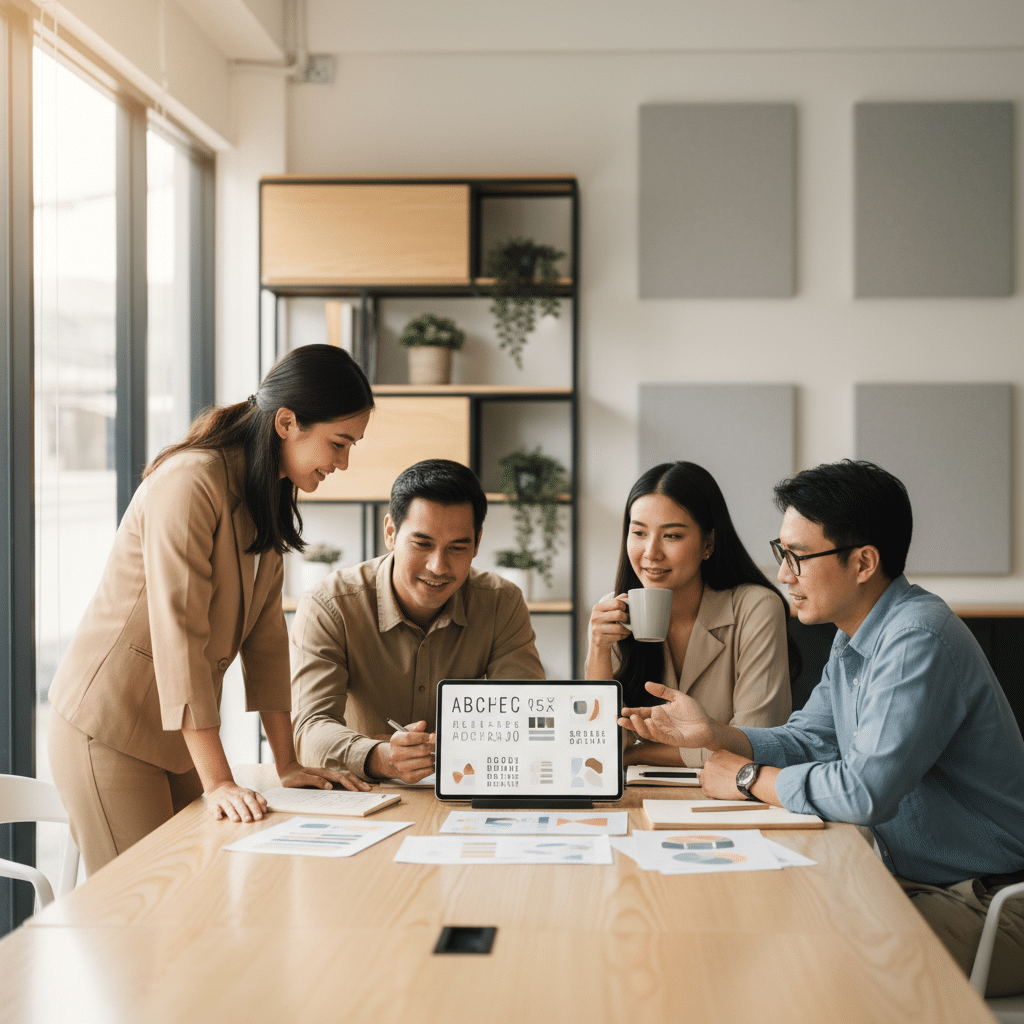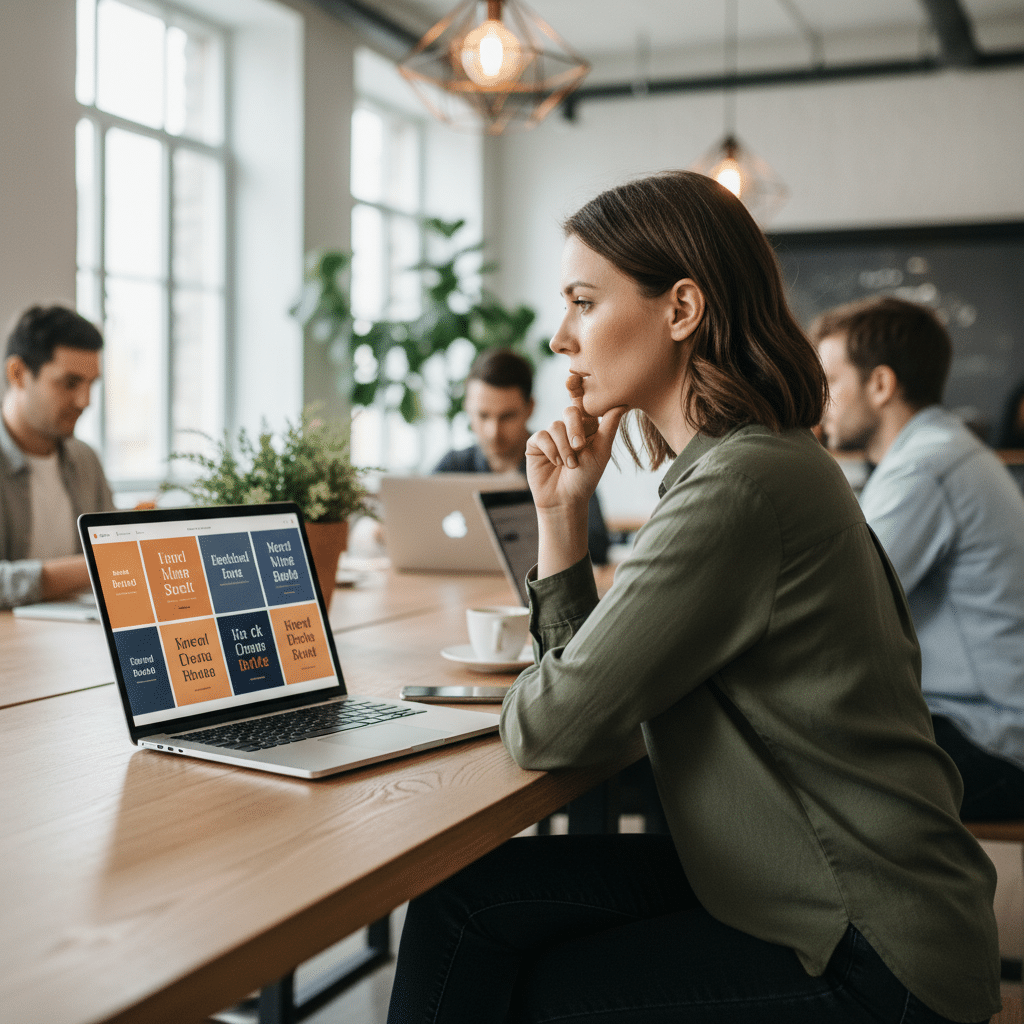
เลือกฟอนต์ผิด ชีวิตเปลี่ยน! จิตวิทยาฟอนต์สำหรับ SME
การเลือกใช้ฟอนต์ในการสร้างแบรนด์สำหรับธุรกิจขนาดกลางและขนาดย่อม (SME) ไม่ใช่เพียงเรื่องของความสวยงาม แต่เป็นเครื่องมือเชิงจิตวิทยาที่ทรงพลังในการสื่อสารบุคลิกภาพและสร้างความน่าเชื่อถือให้กับแบรนด์ การตัดสินใจเลือกฟอนต์สามารถส่งผลกระทบโดยตรงต่อการรับรู้ของลูกค้าและกำหนดทิศทางความสำเร็จของธุรกิจได้
- ฟอนต์มีอิทธิพลโดยตรงต่ออารมณ์ การรับรู้ และความทรงจำของลูกค้าที่มีต่อแบรนด์
- ฟอนต์ประเภท Serif (มีหัว) มักสื่อถึงความน่าเชื่อถือ ความเป็นทางการ และความคลาสสิก เหมาะสำหรับธุรกิจที่ต้องการสร้างภาพลักษณ์ที่มั่นคง
- ฟอนต์ประเภท Sans-Serif (ไม่มีหัว) สื่อถึงความทันสมัย ความเรียบง่าย และความเป็นมิตร เหมาะสำหรับแบรนด์ที่ต้องการเข้าถึงกลุ่มคนรุ่นใหม่
- การเลือกฟอนต์ที่สอดคล้องกับบุคลิกของแบรนด์สามารถเพิ่มการรับรู้คุณค่าและความโดดเด่นในตลาดได้อย่างมีนัยสำคัญ
- SME ควรเลือกฟอนต์โดยพิจารณาจากเป้าหมายของแบรนด์และกลุ่มลูกค้าเป็นหลัก แทนที่จะเลือกจากความชอบส่วนตัวเพียงอย่างเดียว
ประเด็นเรื่อง เลือกฟอนต์ผิด ชีวิตเปลี่ยน! จิตวิทยาฟอนต์สำหรับ SME เป็นมากกว่าแค่การเลือกตัวอักษรที่สวยงาม แต่เป็นการตัดสินใจเชิงกลยุทธ์ที่สามารถกำหนดการรับรู้ของลูกค้าที่มีต่อแบรนด์ได้ตั้งแต่แรกเห็น ฟอนต์ทำหน้าที่เป็น “เสียง” ที่มองเห็นได้ของแบรนด์ สื่อสารบุคลิกภาพ ค่านิยม และสร้างความรู้สึกไว้วางใจหรือความแปลกแยกได้ก่อนที่ลูกค้าจะอ่านข้อความทั้งหมดเสียอีก สำหรับธุรกิจ SME ที่มีทรัพยากรจำกัด การเลือกฟอนต์ที่ถูกต้องจึงเป็นเครื่องมือทางการตลาดที่คุ้มค่าและทรงพลังอย่างยิ่งในการสร้างความแตกต่างและความได้เปรียบในตลาดที่มีการแข่งขันสูง
ทำไมการเลือกฟอนต์จึงสำคัญอย่างยิ่งต่อธุรกิจ SME
ในโลกธุรกิจปัจจุบันที่ผู้บริโภคถูกรายล้อมด้วยข้อมูลและสื่อโฆษณามากมาย การสร้างความประทับใจแรก (First Impression) คือหัวใจสำคัญของการสร้างแบรนด์ให้เป็นที่จดจำ สำหรับธุรกิจ SME การเลือกฟอนต์ที่เหมาะสมเปรียบเสมือนการเลือกเสื้อผ้าให้แบรนด์ เป็นองค์ประกอบแรกที่ลูกค้าสัมผัสและสร้างการรับรู้ในทันที ฟอนต์ที่ไม่เหมาะสมอาจทำให้แบรนด์ดูไม่น่าเชื่อถือ ไม่เป็นมืออาชีพ หรือสื่อสารบุคลิกภาพผิดเพี้ยนไปจากที่ตั้งใจไว้ ในทางกลับกัน ฟอนต์ที่เลือกมาอย่างดีจะช่วยเสริมสร้างภาพลักษณ์ที่แข็งแกร่ง สร้างความไว้วางใจ และดึงดูดกลุ่มเป้าหมายที่ใช่ได้อย่างมีประสิทธิภาพ
ผู้ประกอบการ SME นักการตลาด และนักออกแบบกราฟิกคือกลุ่มที่ต้องให้ความสำคัญกับเรื่องนี้เป็นพิเศษ เพราะการตัดสินใจเลือกฟอนต์จะปรากฏอยู่ในทุกช่องทางการสื่อสาร ตั้งแต่โลโก้ นามบัตร บรรจุภัณฑ์ ป้ายหน้าร้าน ไปจนถึงเว็บไซต์และโซเชียลมีเดีย การเลือกฟอนต์จึงไม่ใช่กระบวนการที่เกิดขึ้นครั้งเดียว แต่เป็นรากฐานของการสื่อสารด้วยภาพทั้งหมดของแบรนด์ การลงทุนเวลาเพื่อศึกษาและทำความเข้าใจจิตวิทยาของฟอนต์จึงเป็นการลงทุนที่คุ้มค่า เพื่อให้แน่ใจว่าทุกสารที่ส่งออกไปนั้นสอดคล้องกับเป้าหมายทางธุรกิจและสร้างผลกระทบเชิงบวกสูงสุด
เจาะลึกจิตวิทยาฟอนต์: เสียงที่มองไม่เห็นของแบรนด์
จิตวิทยาฟอนต์ (Font Psychology) คือการศึกษาว่ารูปแบบตัวอักษรต่างๆ ส่งผลต่อความคิด ความรู้สึก และพฤติกรรมของผู้คนอย่างไรโดยไม่รู้ตัว มันคือศาสตร์และศิลป์ของการสื่อสารเชิงอารมณ์ผ่านรูปทรงของตัวอักษร ฟอนต์แต่ละแบบมีบุคลิกเฉพาะตัวที่สามารถกระตุ้นการรับรู้ที่แตกต่างกันในสมองของมนุษย์ ทำให้ฟอนต์กลายเป็นเครื่องมือที่ทรงพลังในการสร้างบรรยากาศและกำหนดทิศทางการรับรู้ของแบรนด์
การทำงานของจิตวิทยาฟอนต์
สมองของมนุษย์มีความสามารถในการเชื่อมโยงรูปทรงต่างๆ เข้ากับประสบการณ์และความทรงจำที่ผ่านมา ตัวอย่างเช่น เส้นโค้งมนมักให้ความรู้สึกสบาย อ่อนโยน และเป็นมิตร ในขณะที่เส้นตรงและมุมแหลมคมมักให้ความรู้สึกมั่นคง เป็นระเบียบ และจริงจัง หลักการนี้ถูกนำมาใช้กับฟอนต์เช่นกัน ฟอนต์ที่มีลักษณะโค้งมนจะให้ความรู้สึกเข้าถึงง่ายและเป็นกันเอง ส่วนฟอนต์ที่มีโครงสร้างแข็งแรงและเป็นเหลี่ยมมุมจะสื่อถึงความเป็นทางการและความน่าเชื่อถือ
การเลือกฟอนต์เป็นมากกว่าการเลือกตัวอักษร แต่มันคือการเลือกบุคลิกภาพและเสียงของแบรนด์ที่จะสื่อสารกับลูกค้าในทุกครั้งที่พวกเขามองเห็น
Serif vs. Sans-Serif: ศึกแห่งบุคลิกภาพที่แบรนด์ต้องเลือก
ในการออกแบบกราฟิก ฟอนต์สามารถแบ่งออกเป็นหมวดหมู่ใหญ่ๆ ได้หลายประเภท แต่สองประเภทพื้นฐานที่ SME ควรรู้จักและเข้าใจอย่างลึกซึ้งคือ Serif และ Sans-Serif ซึ่งทั้งสองมีบุคลิกและส่งผลต่อจิตวิทยาของผู้รับสารแตกต่างกันอย่างสิ้นเชิง
ฟอนต์มีหัว (Serif): ตัวแทนแห่งความน่าเชื่อถือและความสง่างาม
ฟอนต์ Serif คือฟอนต์ที่มี “ขีด” หรือ “ฐาน” เล็กๆ (เรียกว่า serif) อยู่ที่ปลายสุดของเส้นตัวอักษร ฟอนต์ประเภทนี้มีประวัติศาสตร์ยาวนาน ย้อนกลับไปถึงยุคตัวพิมพ์ในสมัยโรมัน ทำให้มันมีความเชื่อมโยงกับความดั้งเดิม ความคลาสสิก และความเป็นทางการ แบรนด์ที่ใช้ฟอนต์ Serif มักต้องการสื่อสารความน่าเชื่อถือ ความมีประสบการณ์ ความสง่างาม และความมั่นคง
เหมาะสำหรับ: ธุรกิจที่ต้องการสร้างภาพลักษณ์ที่น่าเชื่อถือและเป็นมืออาชีพ เช่น สถาบันการเงิน สำนักงานกฎหมาย แบรนด์สินค้าหรูหรา ธุรกิจที่มีประวัติยาวนาน หรือสื่อสิ่งพิมพ์ที่ต้องการความอ่านง่ายในเนื้อหาที่เป็นข้อความยาวๆ เช่น หนังสือพิมพ์และนิตยสาร
ฟอนต์ไม่มีหัว (Sans-Serif): สัญลักษณ์แห่งความทันสมัยและเรียบง่าย
“Sans” เป็นคำในภาษาฝรั่งเศสที่แปลว่า “ปราศจาก” ดังนั้น Sans-Serif จึงหมายถึงฟอนต์ที่ “ปราศจากขีด” ที่ปลายตัวอักษร ทำให้มีลักษณะที่ดูสะอาดตา เรียบง่าย และทันสมัย ฟอนต์ประเภทนี้ได้รับความนิยมอย่างสูงในยุคโมเดิร์นและในยุคดิจิทัล เนื่องจากความชัดเจนและความสามารถในการอ่านได้ง่ายบนหน้าจอคอมพิวเตอร์และโทรศัพท์มือถือ แบรนด์ที่ใช้ฟอนต์ Sans-Serif มักต้องการสื่อสารถึงความสดใหม่ ความเป็นมิตร ความตรงไปตรงมา และนวัตกรรม
เหมาะสำหรับ: บริษัทเทคโนโลยี สตาร์ทอัพ แบรนด์แฟชั่นที่เน้นความมินิมอล ธุรกิจที่ต้องการสื่อสารกับกลุ่มคนรุ่นใหม่ หรือการใช้งานบนสื่อดิจิทัลที่ต้องการความชัดเจนและอ่านง่าย
| คุณสมบัติ | ฟอนต์ Serif (มีหัว) | ฟอนต์ Sans-Serif (ไม่มีหัว) |
| บุคลิกภาพ | ดั้งเดิม, เป็นทางการ, น่าเชื่อถือ, สง่างาม, ภูมิฐาน | ทันสมัย, เรียบง่าย, เป็นมิตร, สะอาด, ตรงไปตรงมา |
| ความรู้สึกที่สื่อสาร | ความมั่นคง, ประสบการณ์, ความหรูหรา, ความรู้ | นวัตกรรม, ความสดใหม่, การเข้าถึงง่าย, ความมีประสิทธิภาพ |
| ธุรกิจที่เหมาะสม | ธนาคาร, สำนักงานกฎหมาย, มหาวิทยาลัย, แบรนด์หรู, สำนักพิมพ์ | บริษัทเทคโนโลยี, สตาร์ทอัพ, แบรนด์แฟชั่น, ธุรกิจบริการ, เอเจนซี่โฆษณา |
| การใช้งานที่แนะนำ | เนื้อหาขนาดยาวในสื่อสิ่งพิมพ์, โลโก้ที่เน้นความคลาสสิก, หัวเรื่องที่ต้องการความภูมิฐาน | เนื้อหาบนเว็บไซต์และแอปพลิเคชัน, ป้ายโฆษณา, โลโก้ที่เน้นความทันสมัย, อินโฟกราฟิก |
ผลกระทบที่วัดได้: เมื่อตัวเลขยืนยันความรู้สึก
ผลกระทบของจิตวิทยาฟอนต์ไม่ใช่เป็นเพียงความรู้สึกนามธรรม แต่ยังสามารถวัดผลเป็นตัวเลขที่เป็นรูปธรรมได้ งานวิจัยหลายชิ้นได้แสดงให้เห็นว่าการเลือกฟอนต์ที่ถูกต้องสามารถส่งผลต่อการตัดสินใจและพฤติกรรมของผู้บริโภคได้อย่างมีนัยสำคัญ
จากการศึกษาพบว่า การใช้ฟอนต์ที่เหมาะสมสามารถเพิ่มการรับรู้เกี่ยวกับนวัตกรรมของแบรนด์ได้ถึง 9% และยังสามารถ เพิ่มความโดดเด่นของแบรนด์ในสายตาผู้บริโภคได้อีก 7% ตัวเลขเหล่านี้อาจดูไม่มาก แต่ในตลาดที่มีการแข่งขันสูง ความได้เปรียบเพียงเล็กน้อยก็สามารถสร้างความแตกต่างที่ยิ่งใหญ่ได้ การเลือกฟอนต์ที่สอดคล้องกับสารที่ต้องการสื่อจึงเป็นการเพิ่มโอกาสให้แบรนด์ถูกมองในแง่บวกและเป็นที่จดจำได้ง่ายขึ้น
แนวทางปฏิบัติสำหรับ SME: เลือกฟอนต์อย่างไรให้ตรงใจลูกค้า
สำหรับผู้ประกอบการ SME การเลือกฟอนต์ไม่ควรมาจากความชอบส่วนตัวหรือเลือกเพียงเพราะ “ดูสวย” แต่ควรเป็นกระบวนการที่มีหลักการและเป้าหมายที่ชัดเจน
1. กำหนดบุคลิกภาพของแบรนด์ให้ชัดเจน
ก่อนจะเลือกฟอนต์ ต้องตอบคำถามให้ได้ก่อนว่า “แบรนด์ของเรามีบุคลิกอย่างไร?” ลองใช้คำคุณศัพท์ 3-5 คำมาอธิบายแบรนด์ เช่น เป็นมิตร-เชื่อถือได้-มืออาชีพ, สดใส-สร้างสรรค์-สนุกสนาน, หรือ หรูหรา-พิเศษ-คลาสสิก คำเหล่านี้จะเป็นแนวทางในการเลือกฟอนต์ที่มีบุคลิกสอดคล้องกัน
2. เข้าใจกลุ่มเป้าหมาย
ลูกค้าคือใคร? พวกเขามีไลฟ์สไตล์และความชอบแบบไหน? ฟอนต์ที่ดึงดูดกลุ่มวัยรุ่นอาจไม่เหมาะกับกลุ่มผู้สูงวัย การเลือกฟอนต์ที่สอดคล้องกับความคาดหวังและรสนิยมของกลุ่มเป้าหมายจะช่วยให้แบรนด์สามารถเชื่อมต่อกับพวกเขาได้ดีขึ้น
3. พิจารณาบริบทการใช้งาน
ฟอนต์จะถูกนำไปใช้ที่ไหนบ้าง? บริบทการใช้งานเป็นปัจจัยสำคัญอย่างยิ่งในการตัดสินใจ:
- โลโก้ (Logo): ต้องมีความโดดเด่น เป็นเอกลักษณ์ และยังคงอ่านออกได้ง่ายแม้จะมีขนาดเล็ก
- ฟอนต์สำหรับป้าย (Signage): ความอ่านง่าย (Legibility) จากระยะไกลเป็นสิ่งสำคัญที่สุด ต้องเลือกฟอนต์ที่ชัดเจน ไม่ซับซ้อน
- สื่อสิ่งพิมพ์ (Print Media): สำหรับเนื้อหาขนาดยาว ฟอนต์ Serif มักจะอ่านสบายตากว่า แต่สำหรับหัวข้อหรือข้อความสั้นๆ Sans-Serif ก็เป็นตัวเลือกที่ดี
- สื่อดิจิทัล (Digital Media): ความคมชัดบนหน้าจอ (Readability) คือหัวใจสำคัญ ฟอนต์ Sans-Serif มักจะแสดงผลได้ดีกว่าบนหน้าจอที่มีความละเอียดแตกต่างกัน
ความเสี่ยงของการเลือกฟอนต์ผิด: เมื่อการสื่อสารล้มเหลว
การเลือกฟอนต์ผิดพลาดสามารถสร้างความเสียหายต่อภาพลักษณ์ของแบรนด์ได้อย่างไม่น่าเชื่อ ลองจินตนาการถึงสถานการณ์เหล่านี้:
- ธุรกิจด้านการเงินที่ใช้ฟอนต์ลายมือแบบเด็กๆ: การกระทำนี้จะทำลายความน่าเชื่อถือลงในทันที ลูกค้าจะรู้สึกไม่มั่นใจและไม่กล้าที่จะไว้วางใจให้จัดการเรื่องการเงินของพวกเขา
- ร้านอาหารหรูที่ใช้ฟอนต์หนาๆ แบบโปสเตอร์หนังแอ็คชั่น: ทำให้ลูกค้ารู้สึกสับสนเกี่ยวกับบรรยากาศและระดับของร้าน อาจทำให้กลุ่มเป้าหมายที่ต้องการรู้สึกว่าร้านนี้ไม่เหมาะกับพวกเขา
- แบรนด์สินค้าเด็กที่ใช้ฟอนต์ Serif ที่ดูเป็นทางการและเคร่งขรึม: ทำให้แบรนด์ดูน่าเบื่อ ไม่น่าสนใจ และไม่สามารถสื่อสารถึงความสนุกสนานที่เป็นหัวใจของผลิตภัณฑ์ได้
ในยุคดิจิทัลที่ผู้บริโภคมีความอดทนต่ำ ฟอนต์ที่อ่านยากหรือดูไม่สวยงามบนหน้าจออาจทำให้พวกเขาปิดเว็บไซต์หรือแอปพลิเคชันไปในทันที การเลือกฟอนต์ผิดจึงไม่เพียงแต่ส่งผลเสียต่อภาพลักษณ์ แต่ยังอาจหมายถึงการสูญเสียโอกาสทางธุรกิจโดยตรง
บทสรุป: ฟอนต์คือทูตเงียบของแบรนด์
โดยสรุปแล้ว การเลือกฟอนต์สำหรับธุรกิจ SME เป็นกระบวนการที่ต้องอาศัยทั้งความเข้าใจในหลักการออกแบบและจิตวิทยาของผู้บริโภค มันไม่ใช่เรื่องเล็กน้อยที่สามารถมองข้ามได้ แต่เป็นองค์ประกอบสำคัญที่เป็นรากฐานของการสร้างแบรนด์ ฟอนต์คือทูตเงียบที่ทำงานตลอด 24 ชั่วโมง เพื่อบอกเล่าเรื่องราว บุคลิกภาพ และสร้างความสัมพันธ์กับลูกค้า การลงทุนเวลาและความคิดในการเลือกฟอนต์ที่ “ใช่” จะช่วยให้แบรนด์ SME สามารถสื่อสารได้อย่างตรงจุด สร้างความโดดเด่น และปูทางไปสู่ความสำเร็จในระยะยาวได้อย่างยั่งยืน